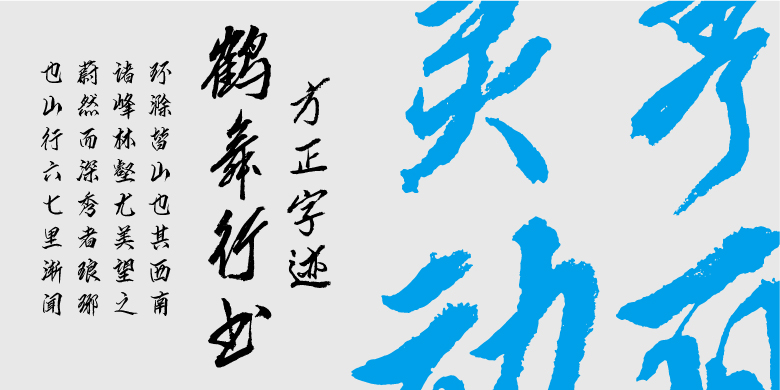
方正字迹-鹤舞行书
方正字迹-鹤舞行书,这款字体结构工整、笔画清晰,兼顾美观与易读性,适用于标题、正文、海报、包装、LOGO 等多种场景。字形优雅稳定,风格百搭耐看,适配日常排版与创意设计,让文字呈现更舒适、更具质感。方正字迹-鹤舞行书一笔一画,皆是细节,以均衡的比例、流畅的线条打造舒适视觉体验,字形端正大气,风格简约现代。无论是商业设计、品牌宣传还是日常排版,都能轻松驾驭,让文字更有格调与力量。方正字迹-鹤舞行书字体下载。
这款行书追求秀丽灵动,流畅隽美,体现了传统的书法韵味、人文情怀和时代之美,也力求展现女性之美。书写规范,辨识度强,适合广泛应用。